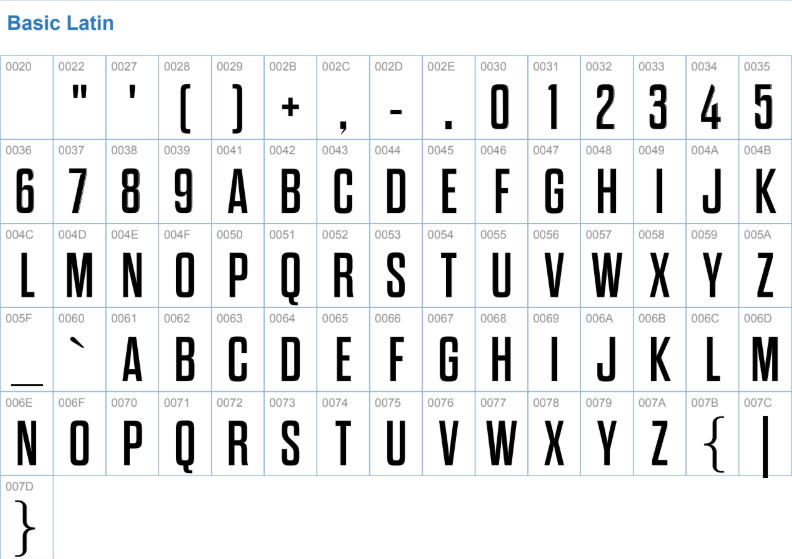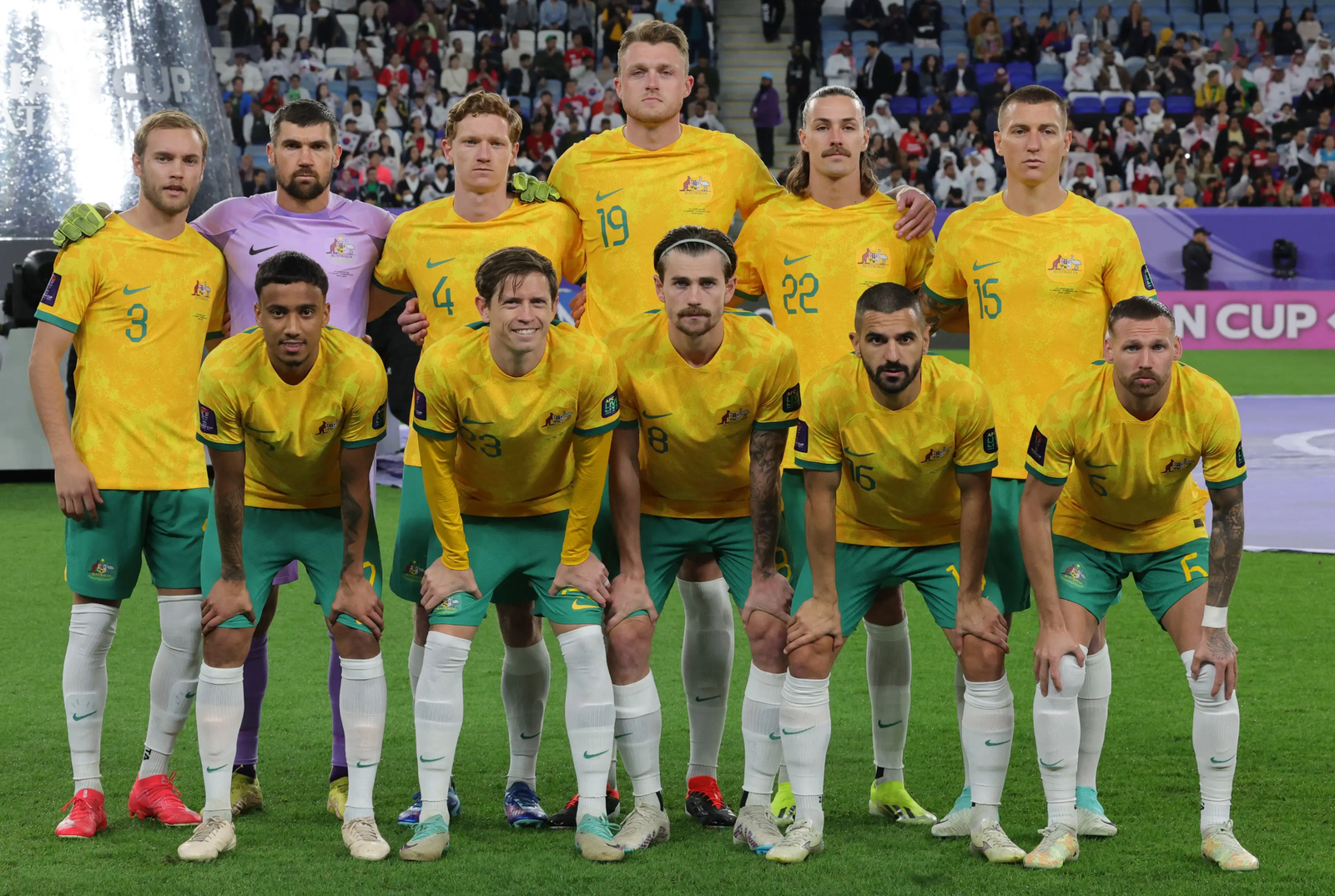
A contagem regressiva para a Copa do Mundo já começou e a Austrália chega com identidade visual completamente reformulada. Os Socceroos apresentaram seu novo uniforme e, com ele, uma tipografia oficial que já está dando o que falar entre designers e torcedores apaixonados por futebol.
Detalhes técnicos da fonte
- Caracteres disponíveis: Caixa alta, números de 0 a 9 e conjunto essencial de pontuação
Estilo visual da tipografia
A nova tipografia abandona curvas excessivas e investe em formas geométricas imponentes. Os números exibem laterais retas com corte angular pronunciado, criando contraste forte contra o verde do gramado.
O design garante leitura instantânea das arquibancadas e máxima nitidez nas transmissões televisivas. Traços limpos e modernos capturam fidelidade em silk-screen sobre poliéster, mantendo a estética agressiva que combina com o futebol físico da seleção comandada por Graham Arnold.
Aplicação no uniforme
No manto titular verde e dourado, a fonte ganha acabamento metálico que homenageia as conquistas asiáticas. Na versão reserva turquesa, os números assumem tom escuro gerando contraste elegante. Já o terceiro uniforme azul-marinho recebe aplicação em branco com efeito fantasma discreto.